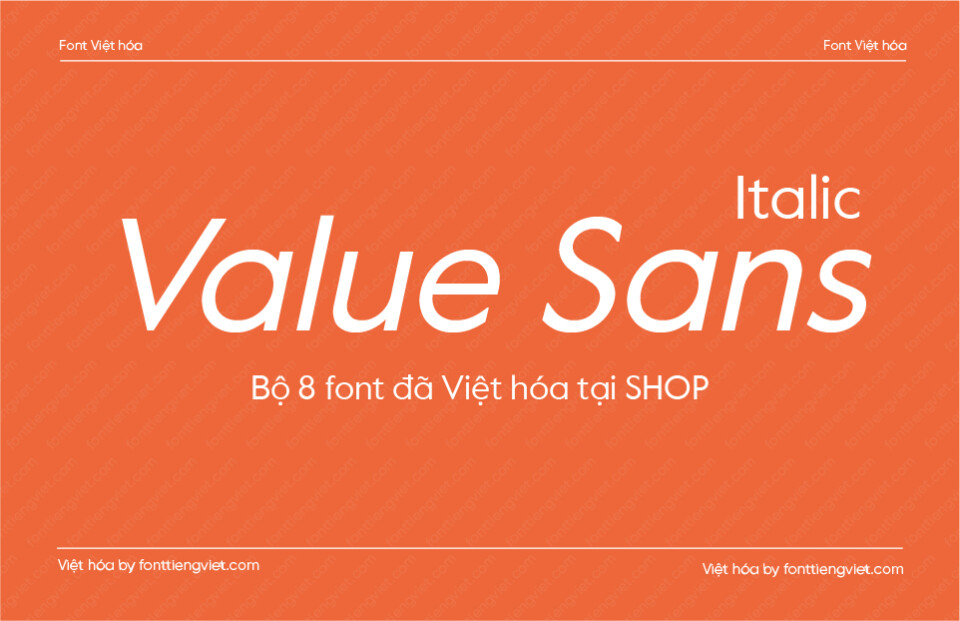
Font Việt hóa 1FTV VIP Value Sans Italic
Font Việt hóa 1FTV VIP Value Sans Italic – Đỉnh Cao Thiết Kế Hiện Đại Cho Mọi Dự Án
Giới thiệu về Font Việt hóa 1FTV VIP Value Sans Italic trong thiết kế hiện đại
Trong thế giới sáng tạo ngày nay, việc lựa chọn một bộ Font Miễn Phí chất lượng đóng vai trò then chốt trong việc tạo dựng bản sắc riêng cho mỗi tác phẩm. Font Việt hóa 1FTV VIP Value Sans Italic nổi lên như một sự lựa chọn hàng đầu cho những ai tìm kiếm sự cân bằng giữa nét trẻ trung, hiện đại và tính chuyên nghiệp cao. Đây là phiên bản in nghiêng đặc sắc thuộc hệ sinh thái font chữ sans-serif tối giản, được điều chỉnh tỉ mỉ để phù hợp hoàn hảo với hệ thống dấu tiếng Việt mà không làm mất đi cấu trúc hình học nguyên bản của bộ chữ quốc tế.
Những đặc điểm nổi bật của Font Việt hóa 1FTV VIP Value Sans Italic
Thiết kế nghiêng tinh tế và thanh thoát
Điểm mạnh nhất của Font Việt hóa 1FTV VIP Value Sans Italic chính là độ nghiêng được tính toán kỹ lưỡng, tạo cảm giác chuyển động nhẹ nhàng và tinh tế. Không giống như những font chữ in nghiêng phổ thông thường gây cảm giác xô lệch, bộ font này duy trì được độ mở của các chữ cái, giúp nội dung luôn rõ ràng ngay cả ở kích thước nhỏ. Sự thanh thoát này khiến nó trở nên cực kỳ hữu dụng trong việc nhấn mạnh các trích dẫn quan trọng hoặc tạo điểm nhấn trong các tiêu đề phụ của bài thuyết trình học đường.
Khả năng hiển thị tối ưu trên đa nền tảng
Nhờ cấu trúc sans-serif (không chân), Font Việt hóa 1FTV VIP Value Sans Italic mang lại trải nghiệm đọc mượt mà trên cả màn hình kỹ thuật số lẫn bản in truyền thống. Các nét chữ đồng đều về độ dày giúp giảm mỏi mắt, một yếu tố rất quan trọng khi áp dụng vào các tài liệu giáo dục hoặc nội dung bài giảng trực tuyến. Sự hiện đại của nó cũng giúp các trang web trở nên chuyên nghiệp và bắt kịp xu hướng thiết kế tối giản đang thịnh hành trên toàn cầu.
Ứng dụng thực tiễn của Font Việt hóa 1FTV VIP Value Sans Italic
Sáng tạo nội dung cho học sinh và nhà trường
Đối với môi trường giáo dục, bộ font này là công cụ đắc lực để làm mới các mẫu báo tường, slide bài giảng hoặc bằng khen. Vẻ ngoài năng động của Font Việt hóa 1FTV VIP Value Sans Italic kích thích sự hứng thú và sáng tạo cho học sinh, đồng thời giữ được sự nghiêm túc cần thiết của một văn bản sư phạm. Thầy cô có thể dễ dàng kết hợp nó với các biến thể Bold hoặc Regular để tạo nên một hệ thống phân cấp thông tin khoa học và dễ hiểu.
Thiết kế thương hiệu và quảng cáo
Bên cạnh mục đích học tập, các nhà thiết kế tự do cũng thường xuyên sử dụng bộ font này cho các dự án nhận diện thương hiệu. Từ logo, bao bì sản phẩm đến các ấn phẩm truyền thông mạng xã hội, nét nghiêng của 1FTV VIP Value Sans Italic luôn mang lại cảm giác thời thượng và cao cấp. Khả năng tương thích tốt với các phần mềm đồ họa chuyên nghiệp giúp quy trình làm việc trở nên nhanh chóng và hiệu quả hơn bao giờ hết.
Kết luận và cách sở hữu Font Việt hóa 1FTV VIP Value Sans Italic